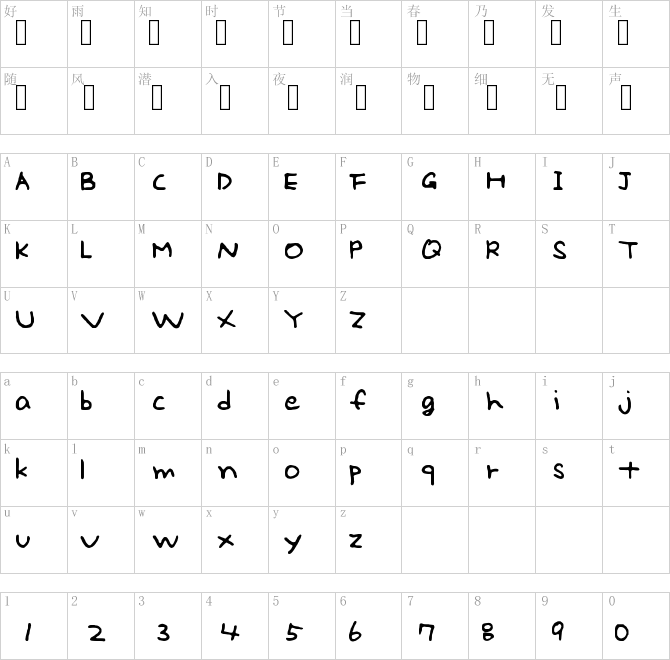
나눔손글씨 예쁜 민경체韩国字体
나눔손글씨 예쁜 민경체韩国字体,这款字体结构工整、笔画清晰,兼顾美观与易读性,适用于标题、正文、海报、包装、LOGO 等多种场景。字形优雅稳定,风格百搭耐看,适配日常排版与创意设计,让文字呈现更舒适、更具质感。나눔손글씨 예쁜 민경체韩国字体一笔一画,皆是细节,以均衡的比例、流畅的线条打造舒适视觉体验,字形端正大气,风格简约现代。无论是商业设计、品牌宣传还是日常排版,都能轻松驾驭,让文字更有格调与力量。나눔손글씨 예쁜 민경체韩国字体字体下载。
• 字体名称:나눔손글씨 예쁜 민경체
• 字体风格:Regular
• 字体标识:CLOVA OCR : Nanum YeBbeunMinGyeongCe
• 字体全称:나눔손글씨 예쁜 민경체